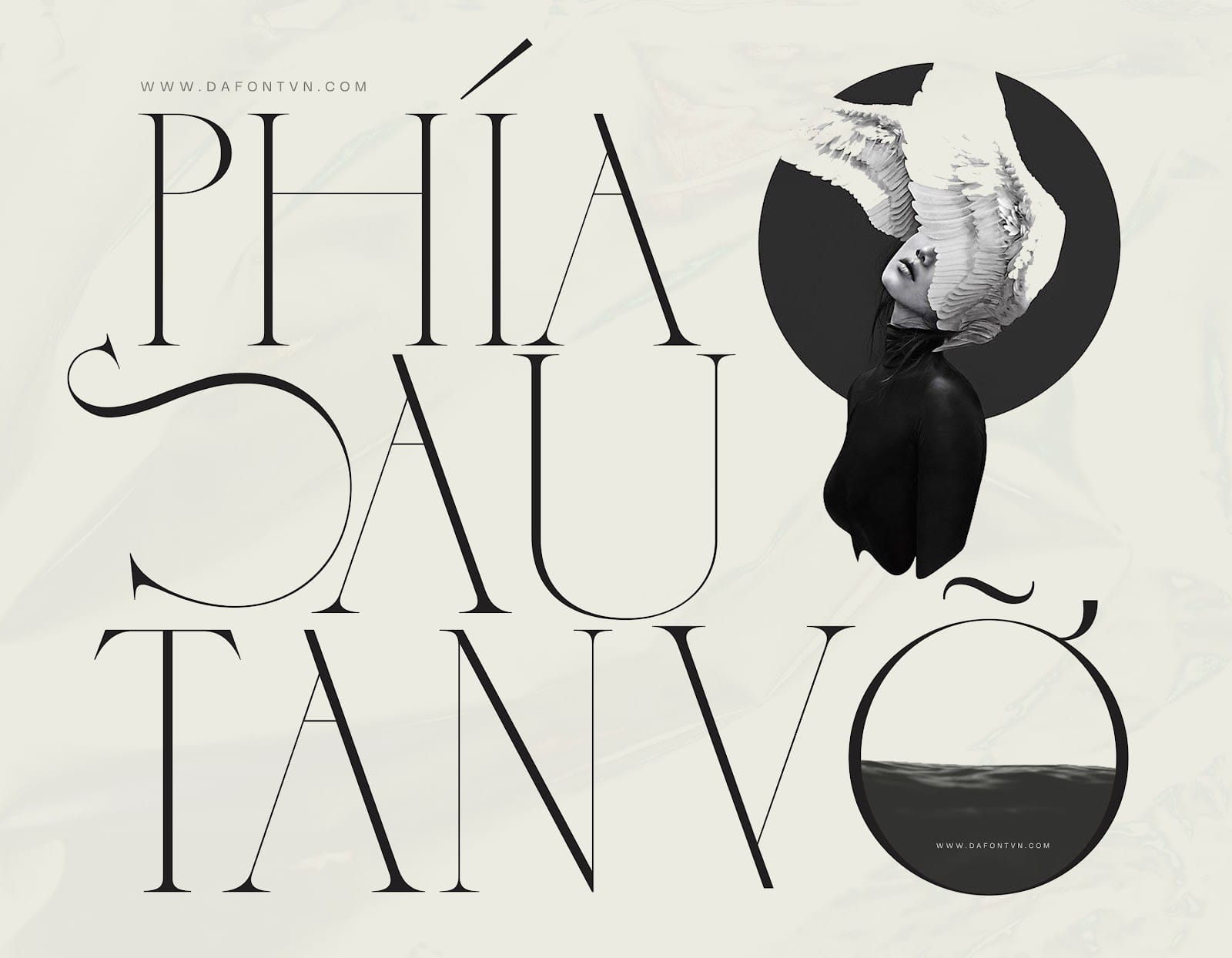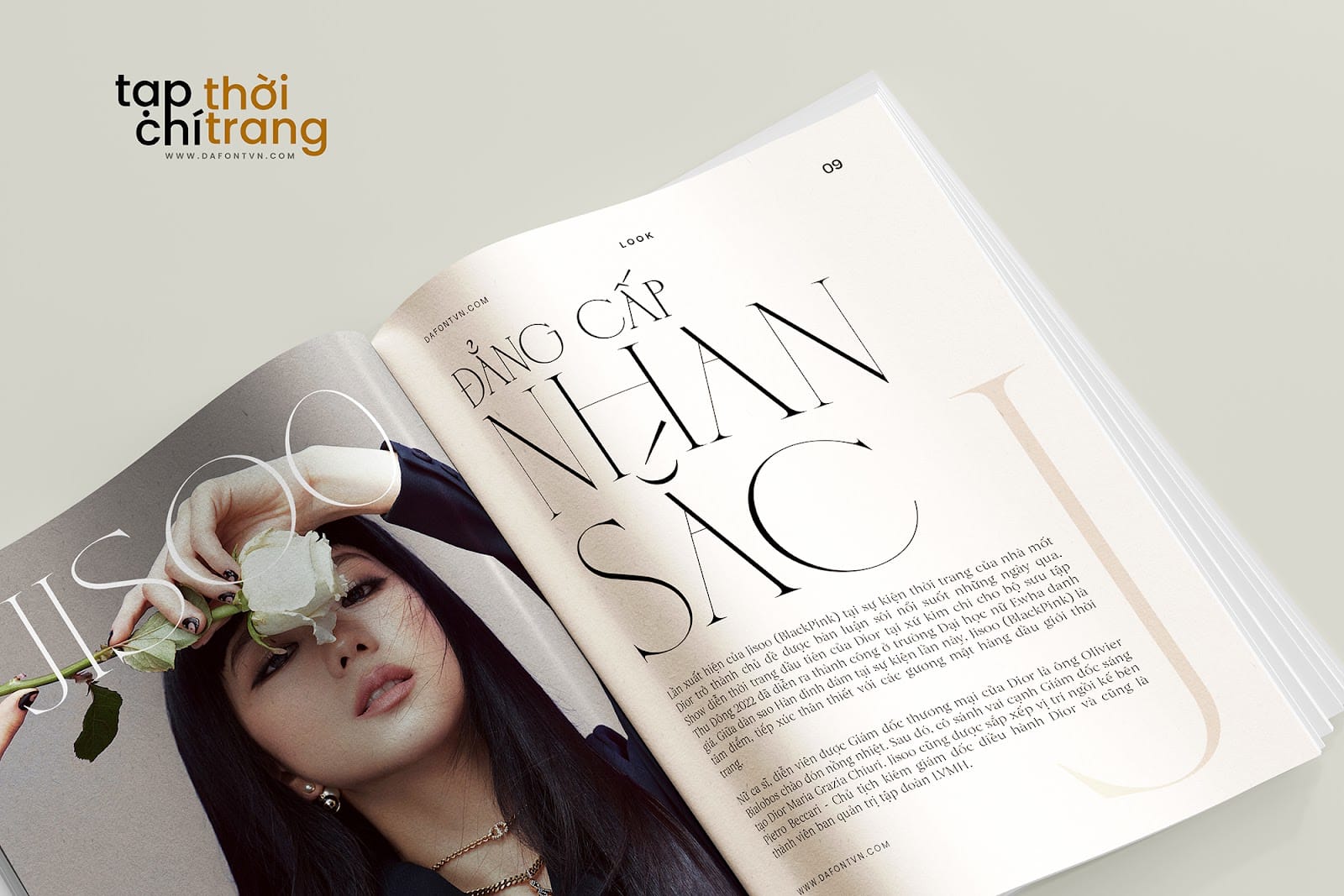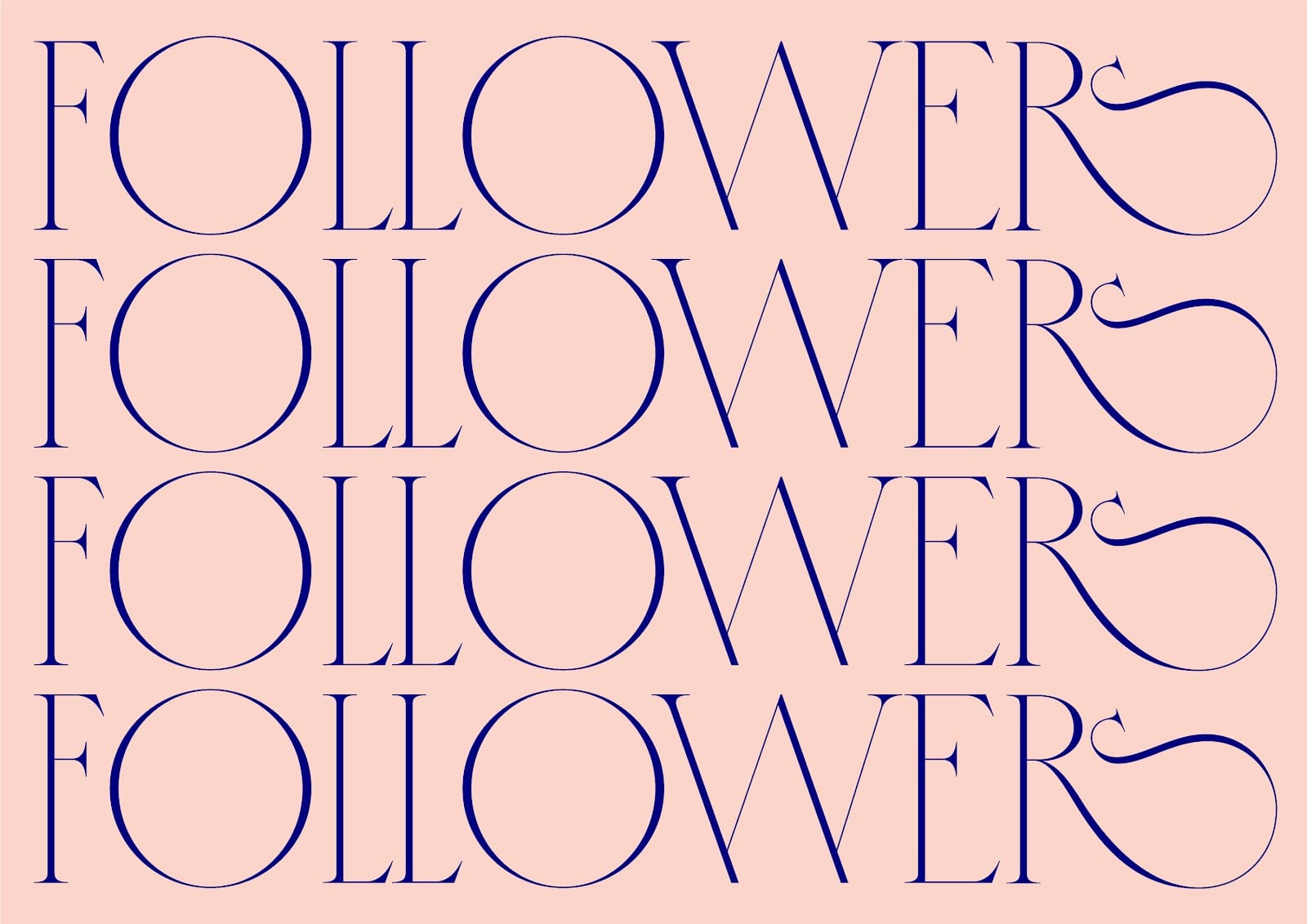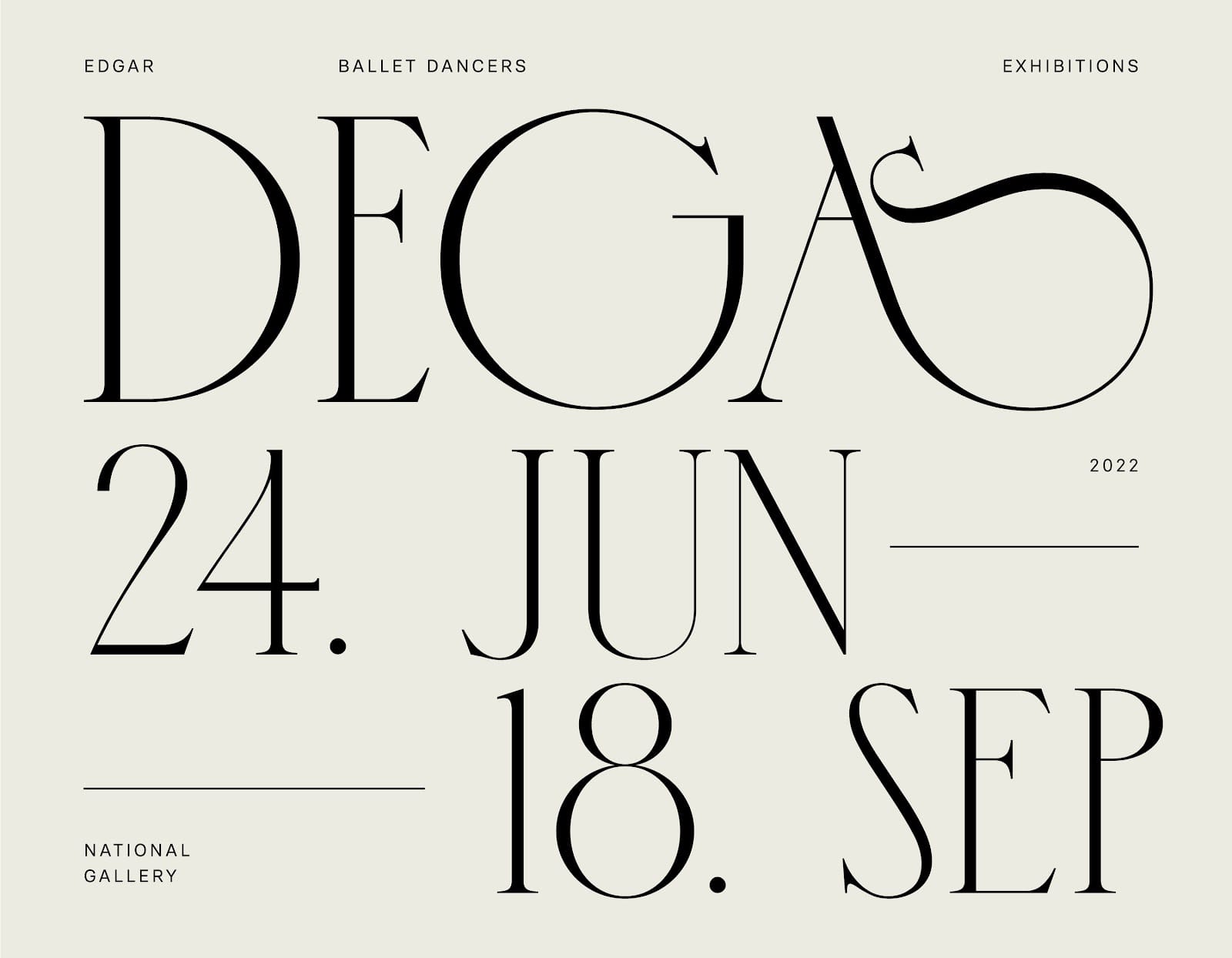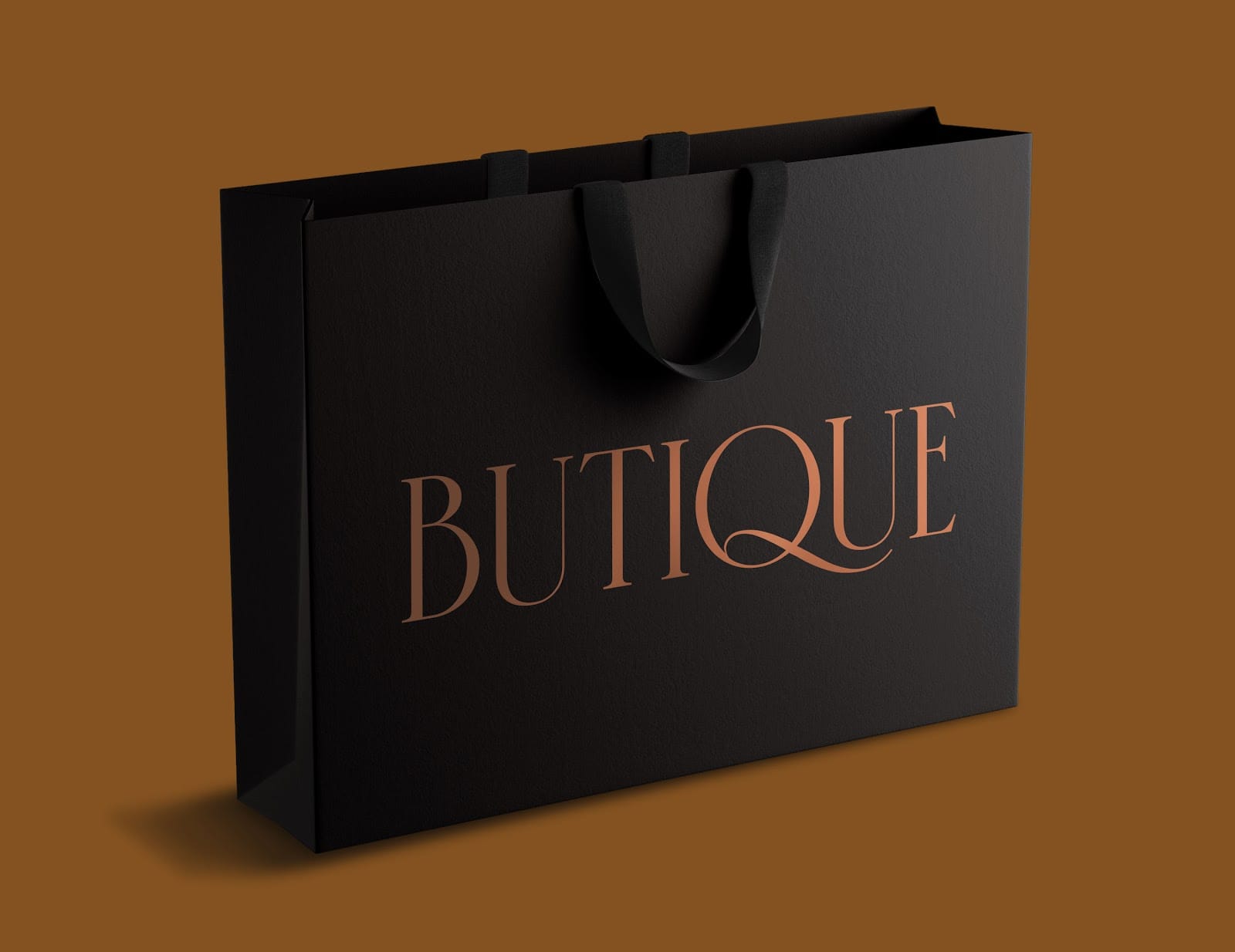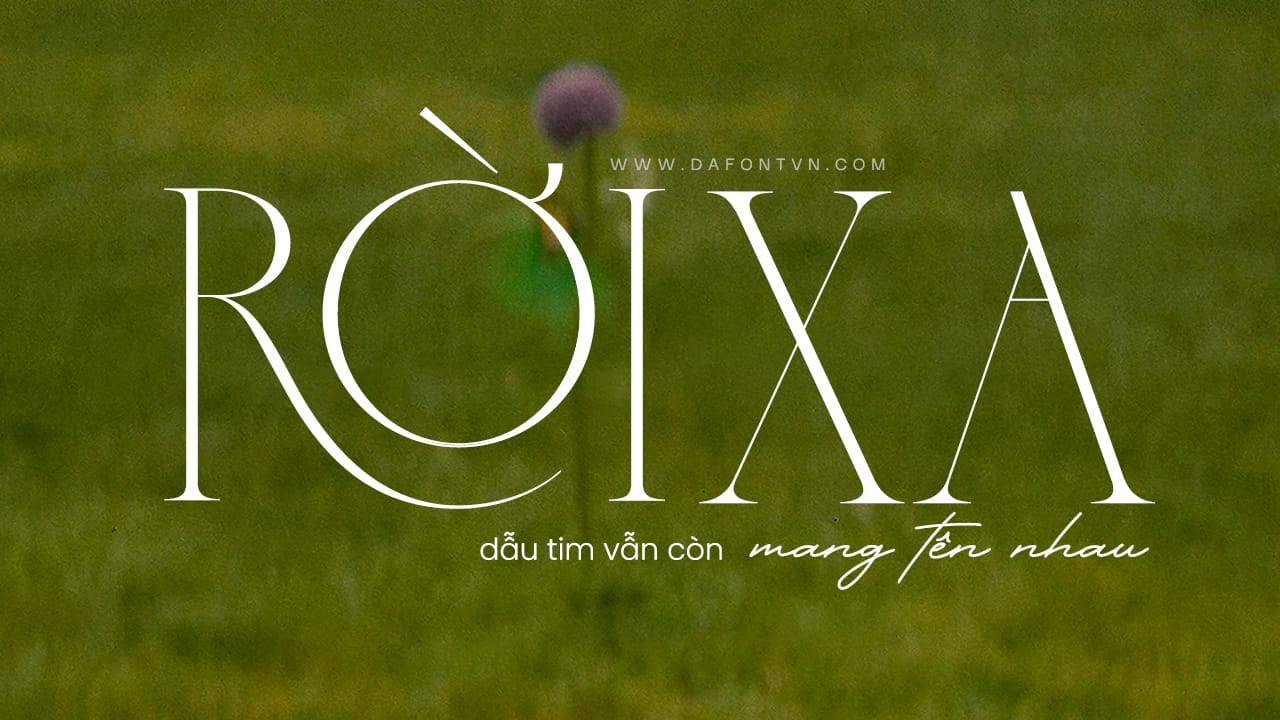
Chloé Typeface một kiểu chữ hiện đại với các ký tự được viết hoa toàn bộ, các nét chữ được thiết kế thanh mảnh và đẹp mắt, đi kèm với nó là một loạt các ký tự mở rộng các các đường cong mềm mại.Đây là một kiểu chữ phù hợp cho tiêu đề lớn, logo, thiết kế bố cục, tạp chí, sản phẩm… Font được việt hóa đầy đủ với 2 kiểu Regular và Bold. Ngoài ra, font cũng được kernng và tối ưu hóa lại.